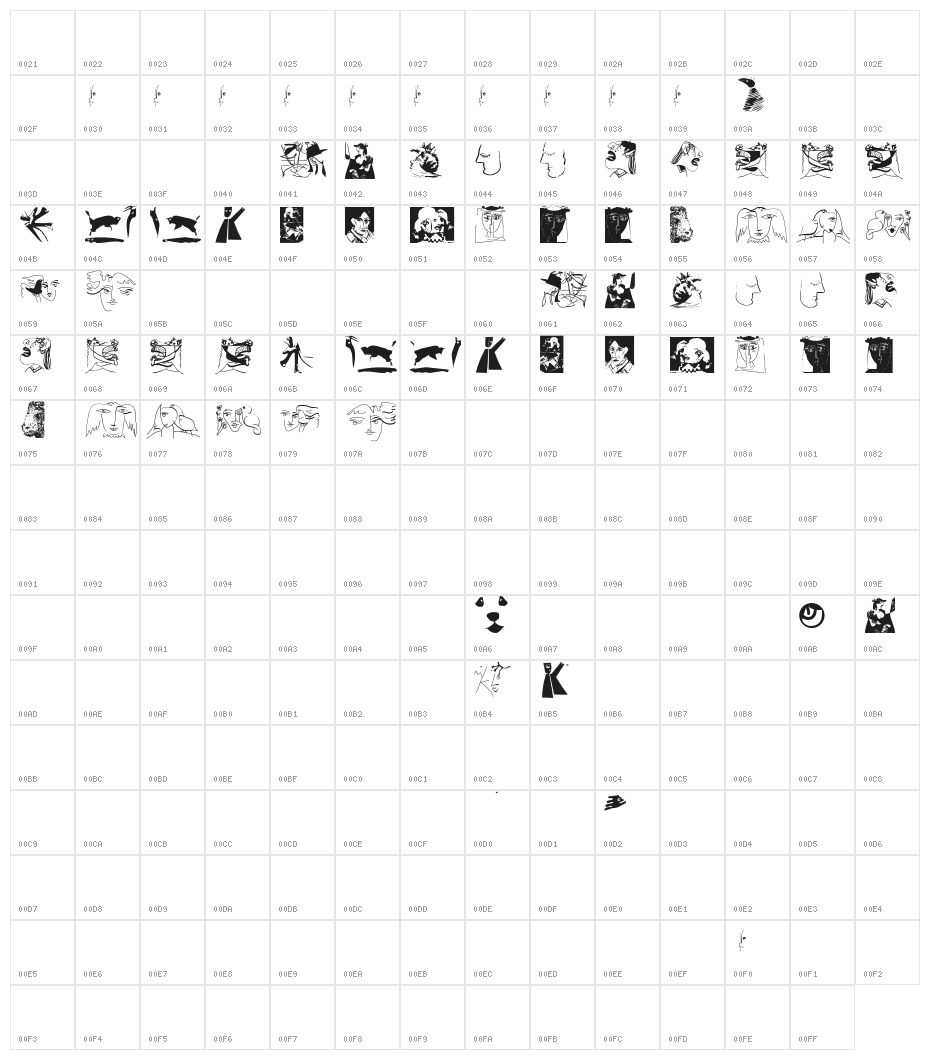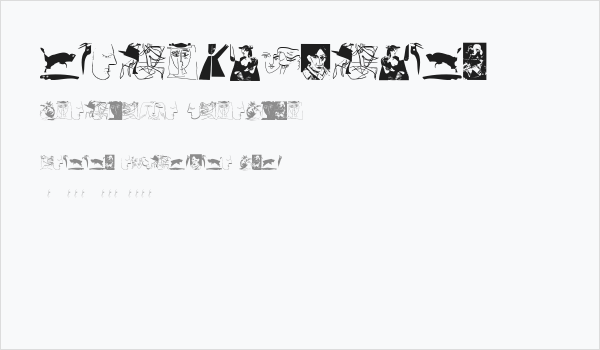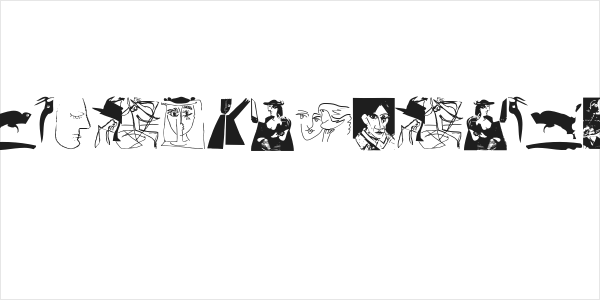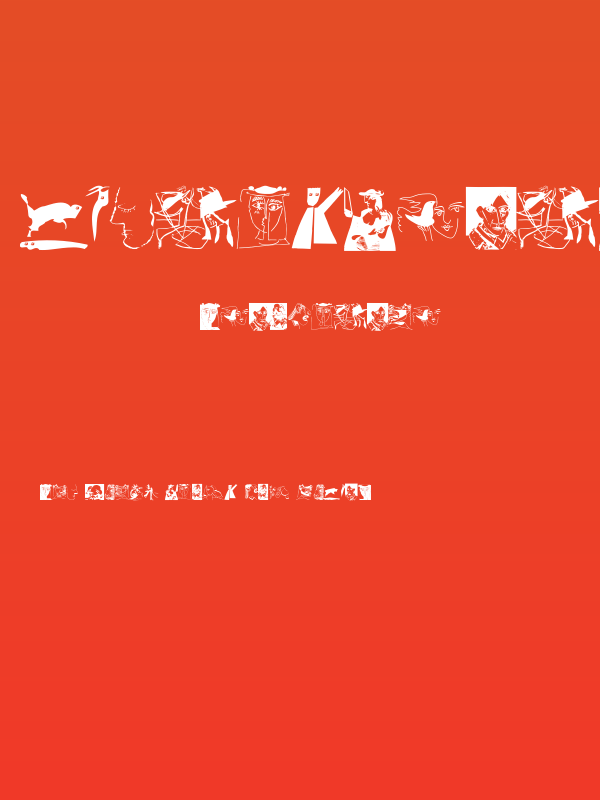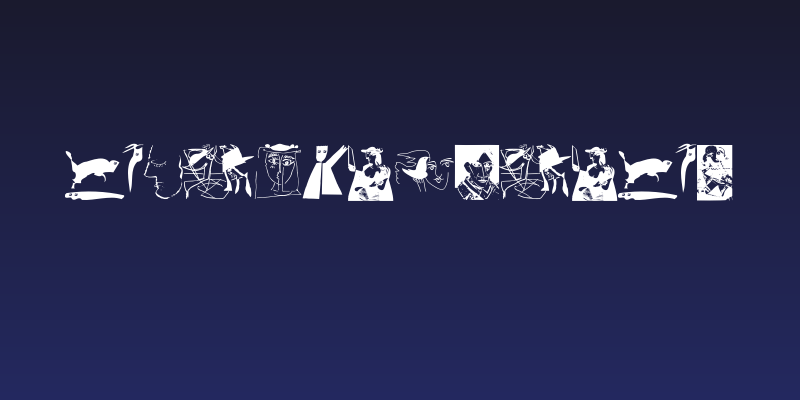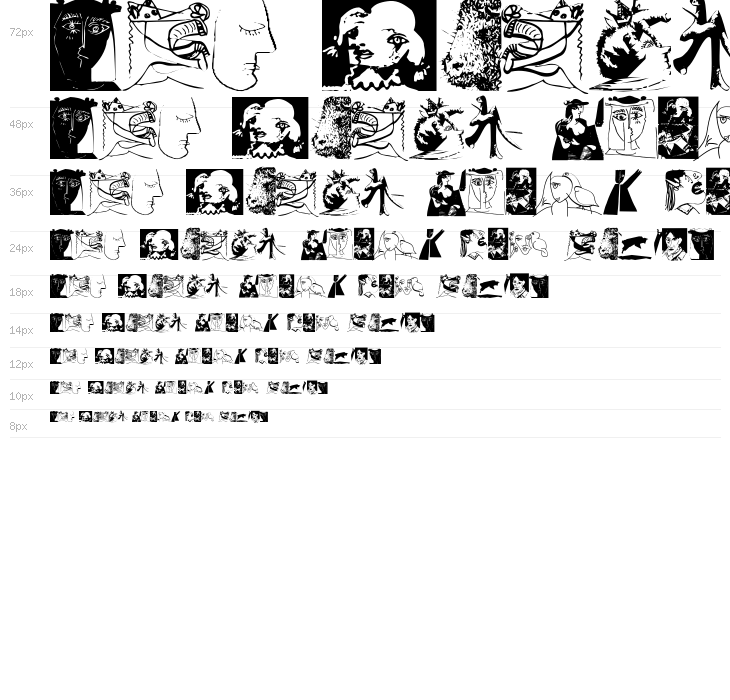
LearnByPablo Font
| Stile generale | Artistic, Abstract, Surreal |
| Caso d'uso | Artistic displays, Creative projects |
| Progetti proposti | Ideal for art projects, creative posters, album covers, and any design work that seeks to incorporate a unique and artistic touch. |